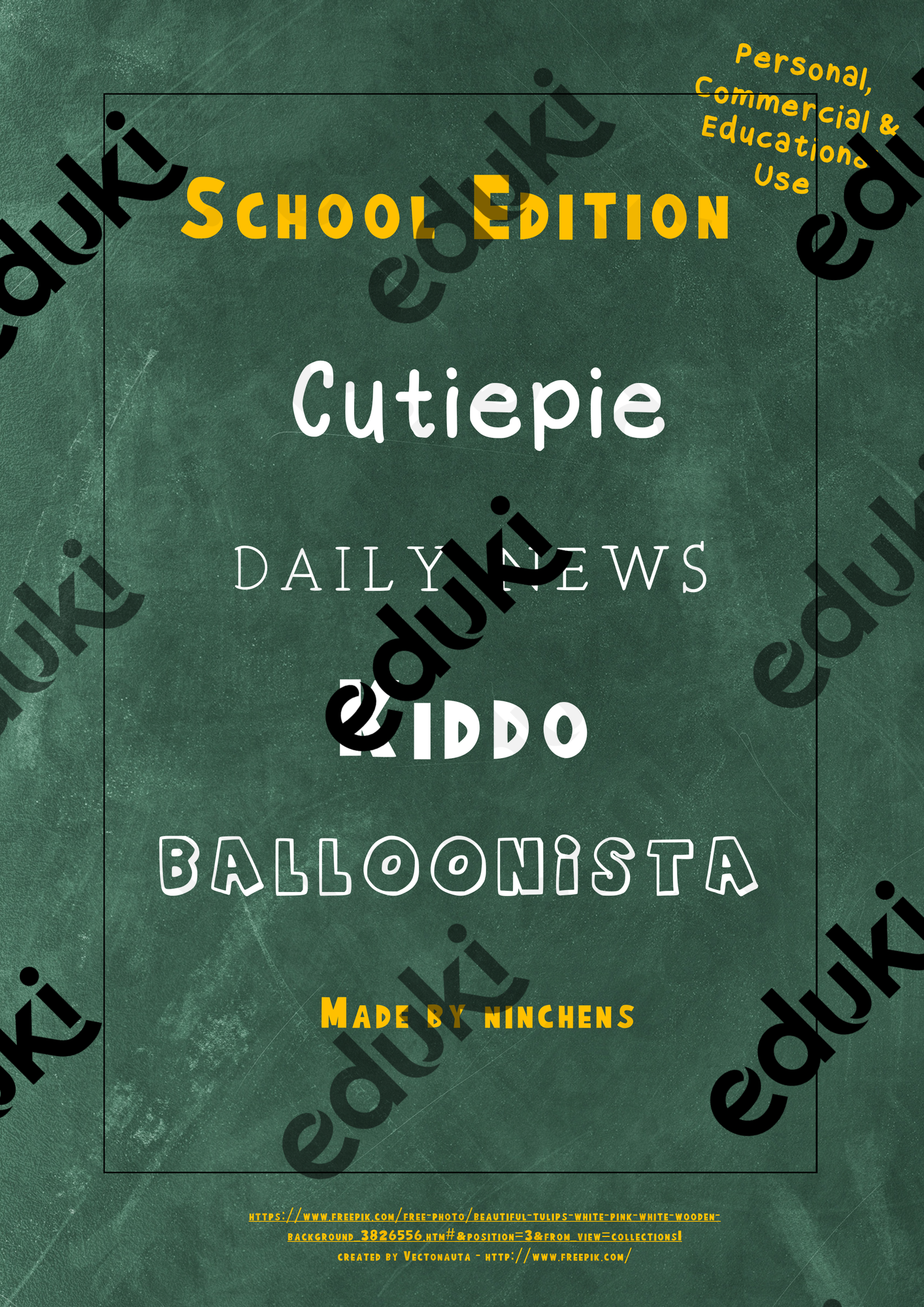
Das ultimative Schriftarten-Set für die Schule. Damit werden alle deine Arbeitsblätter und Präsentationen zu einem Hit. Wähle zwischen den vier Schriftarten cutiepie, daily news, kiddo & balloonista. Mach deinen Schulalltag ästhetisch und anschaulich!